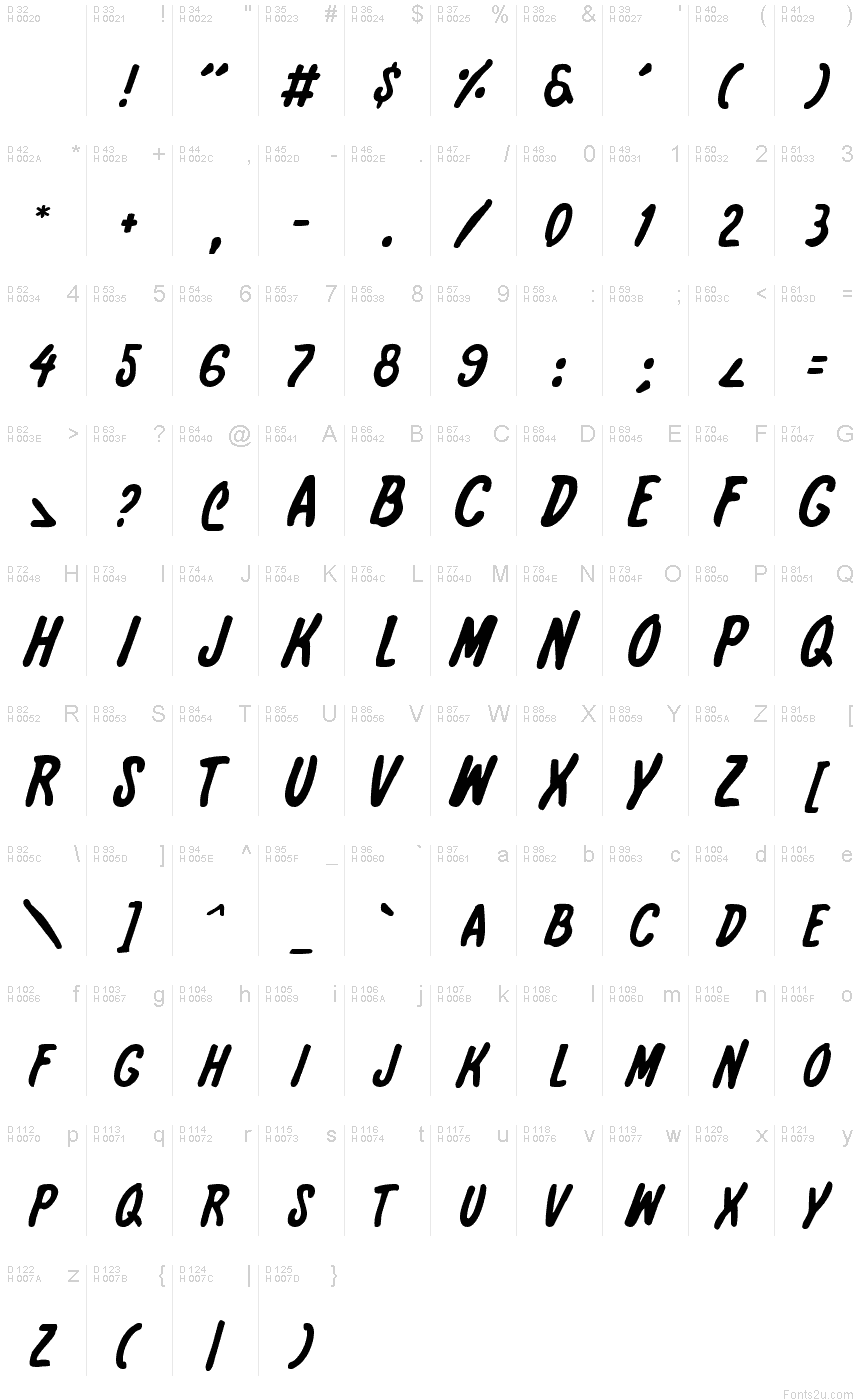
International Super Hero di Iconian Fonts è un font gratuito per fumetti che colpisce con l'energia di una pennellata audace e inchiostrata. Le lettere pendono leggermente in avanti, come se corressero tra le vignette di un fumetto, mentre le curve massicce e i bordi leggermente irregolari mantengono un aspetto giocoso e disegnato a mano. È un font d'impatto, che si fa notare senza essere aggressivo: più un richiamo eroico che un urlo fastidioso.
Con International Super Hero, i tuoi titoli cattureranno subito l'attenzione su copertine di fumetti, locandine di eventi, schermate di avvio di giochi, miniature di YouTube, confezioni di giocattoli e inviti per compleanni o cosplay. Questo font gratuito dà il meglio di sé in grande e centrato, lasciando che i suoi tratti spessi e il ritmo dinamico riempiano la scena. Per il testo di accompagnamento, abbinalo a un carattere sans serif geometrico semplice per mantenere leggibili i titoli ricchi di azione e bilanciare l'impaginazione.